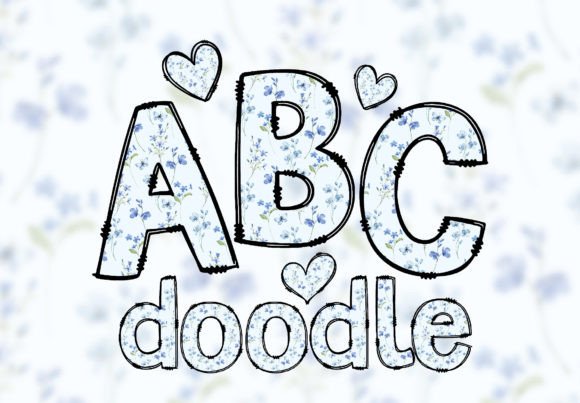
Doodle Floral Alphabet PNG Letters Font
全方位评测:Doodle Floral Alphabet PNG 字体套装
想让你的设计作品瞬间活泼起来吗?Doodle Floral Alphabet PNG Letters Font 以手绘涂鸦风格的字母为核心,为海报、邀请函、贺卡等多种创意项目注入满满的趣味与温度。每个字母均为 PNG 格式、透明背景,300 DPI 超高分辨率(约 2000×2400px),无论是 Photoshop、Illustrator 还是 Canva,都能实现「即插即用」的无缝融合。
产品亮点一目了然
• ✅ 完整字符集:包含 26 大写字母、26 小写字母、0‑9 数字以及 2 个爱心图案,满足绝大多数设计需求。
• ✅ 手绘涂鸦风格:每个字母都配有细腻的花卉 doodle,独特且充满故事感,让文字本身成为视觉焦点。
实际使用场景推荐
• 婚礼邀请函、生日派对请柬——用手绘字母写下温馨祝福。
• 手工卡片、DIY 手账——在每一页加入花卉 doodle,让笔记更具个人风格。
• 商业海报、社交媒体贴图——标题采用 Doodle 字体,瞬间抓住目光。
• 电子贺卡、纪念册——透明 PNG 让文字与背景图层自然融合。
总结
如果你正在寻找一款兼具可爱与艺术感的字体,Doodle Floral Alphabet PNG Letters Font 是不容错过的选择。它的手绘涂鸦元素让文字本身拥有故事性,透明背景和高分辨率保证了在任何设计项目中的灵活运用。立即下载,开启你的创意之旅,让每一个字母都为你的作品加分!